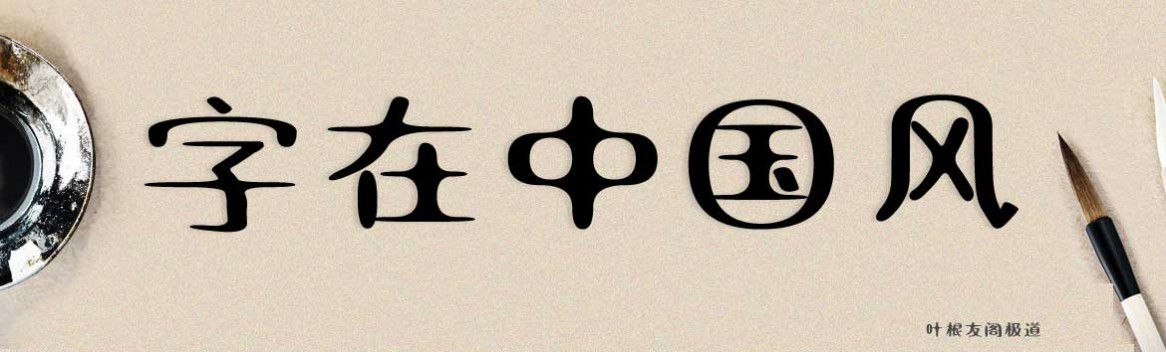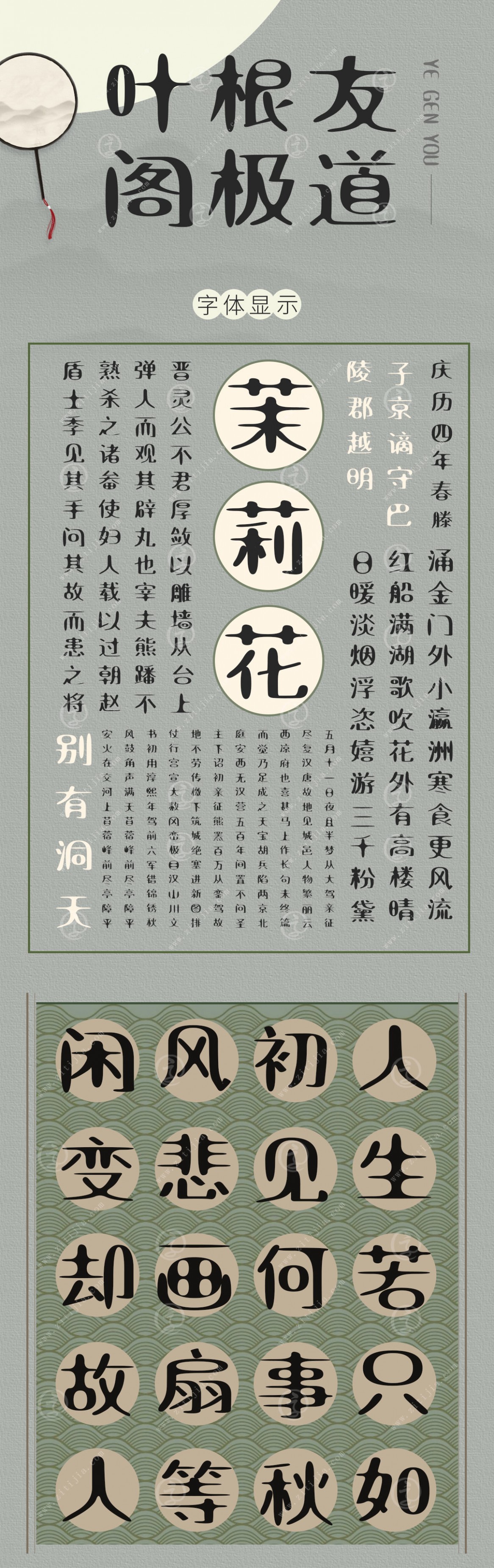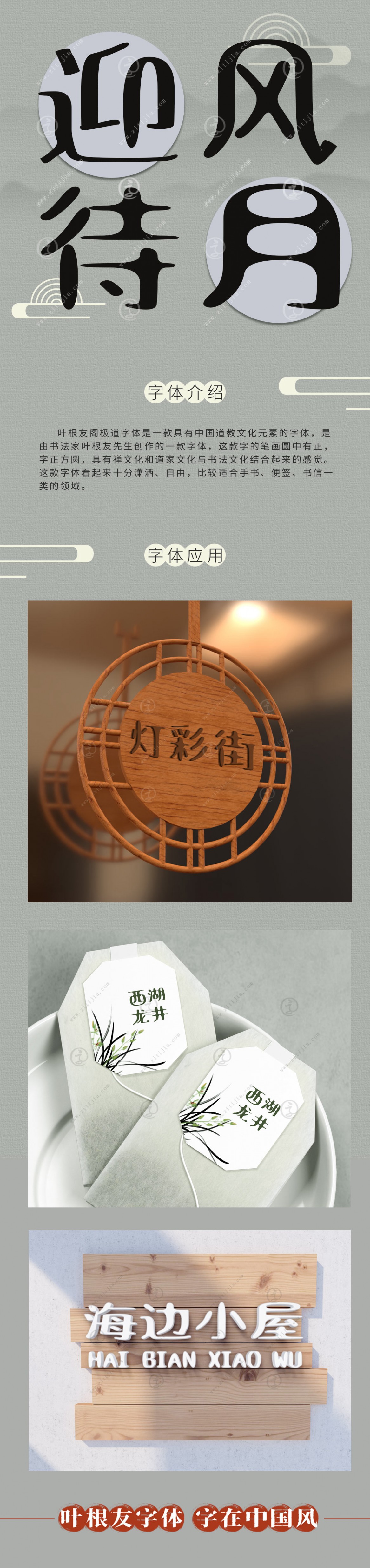
葉根友閣極道
字體作者:葉根友
創(chuàng)作年代:2015年
字體字?jǐn)?shù):6763個(gè)中文漢字以及其他英文字母和阿拉伯?dāng)?shù)字
字體介紹
葉根友閣極道字體是一款具有中國(guó)道教文化元素的字體,字的筆畫圓中有正,字正方圓,具有禪文化和道家文化與書法文化是結(jié)合。